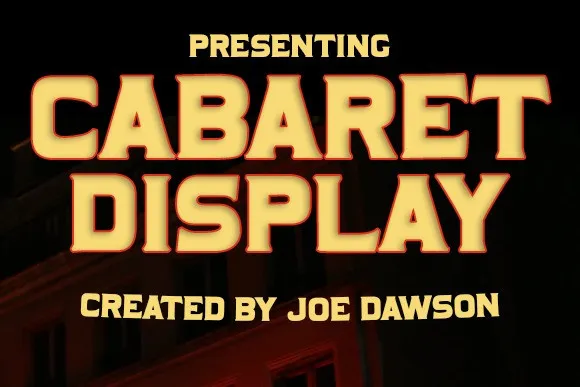
Cabaret Display Font – Download Grátis
Cabaret Display Font é uma nova tipografia para destaque que traz nostalgia à sua produção visual. Esta fonte sans-serif bold leva você a momentos mais simples do passado, lembrando dos ambientes de cabaré de Paris, conhecidos por suas atmosferas modernas e vibrantes. Ideal para projetos que buscam um toque vintage e artístico, seja para títulos de revistas, logomarcas, desenvolvimento de marca ou até mesmo para mensagens empostadas em placas de propaganda. A ideia é dar vida a um estilo retrô moderno, com letras inteiras (all caps) que invocam uma sensação nostálgica e artisticamente envolvente. Cabaret Display Font é perfeita para aqueles que buscam uma linguagem única para expressar suas mensagens em mídias impressas ou digitais.